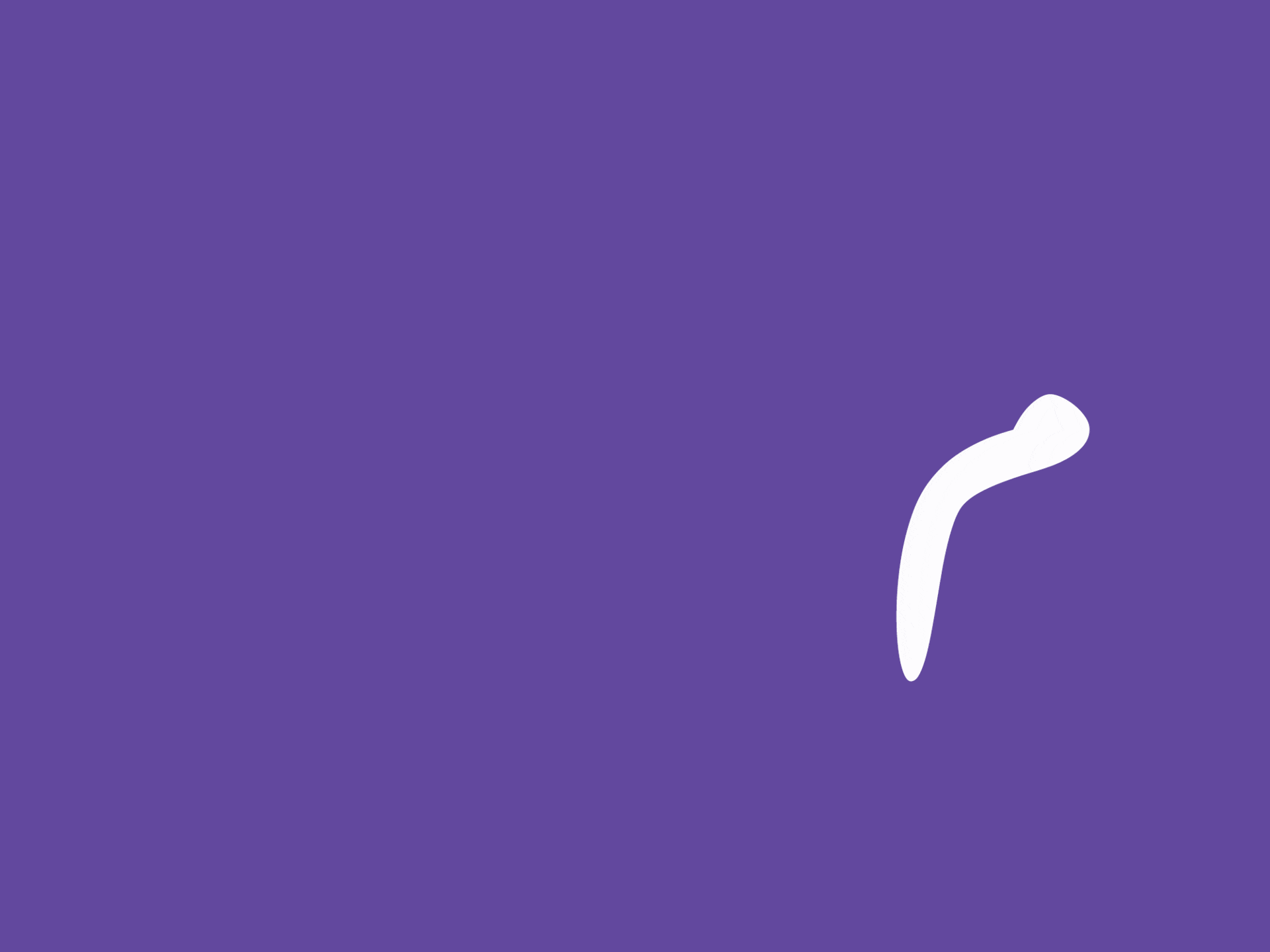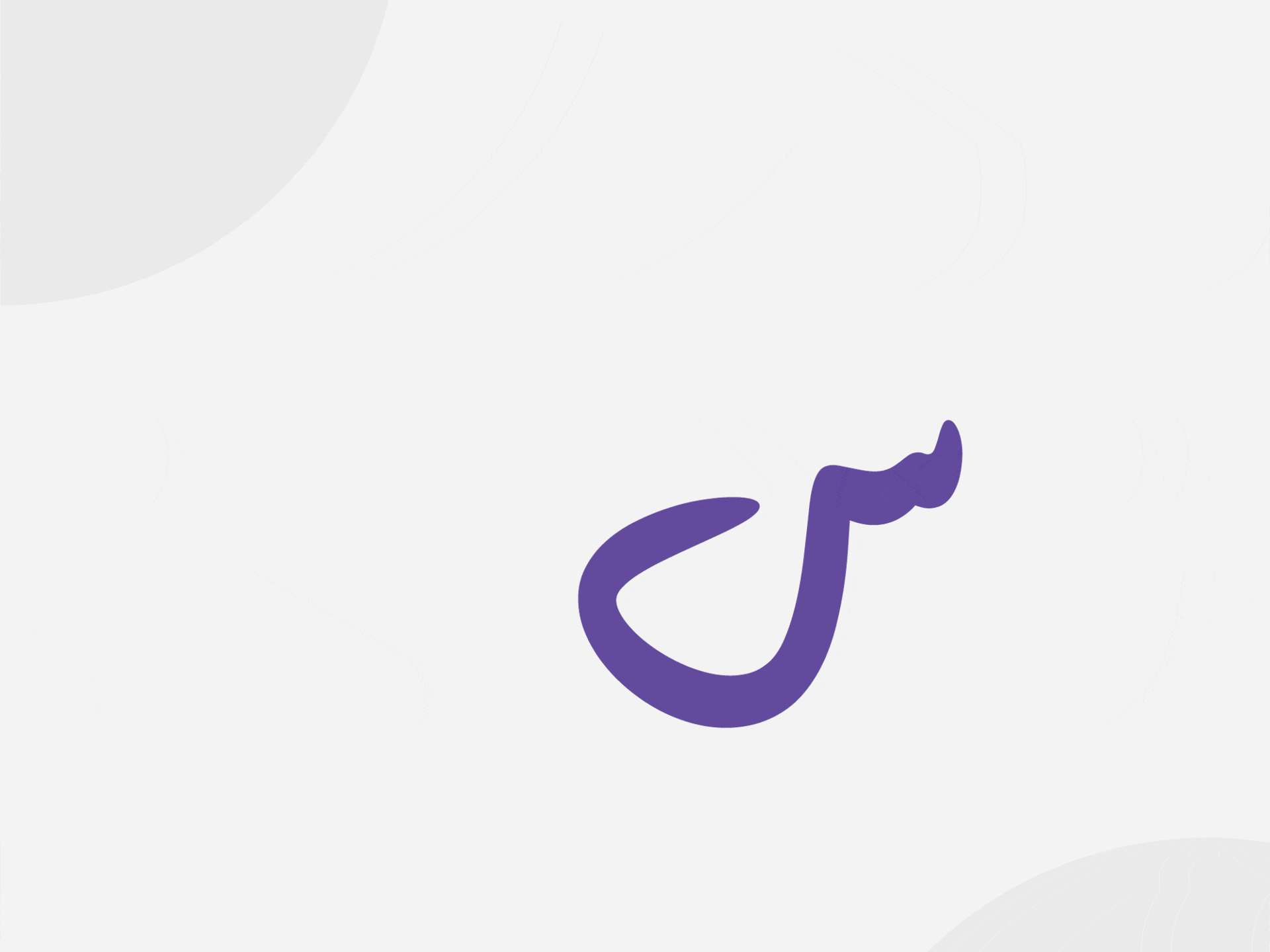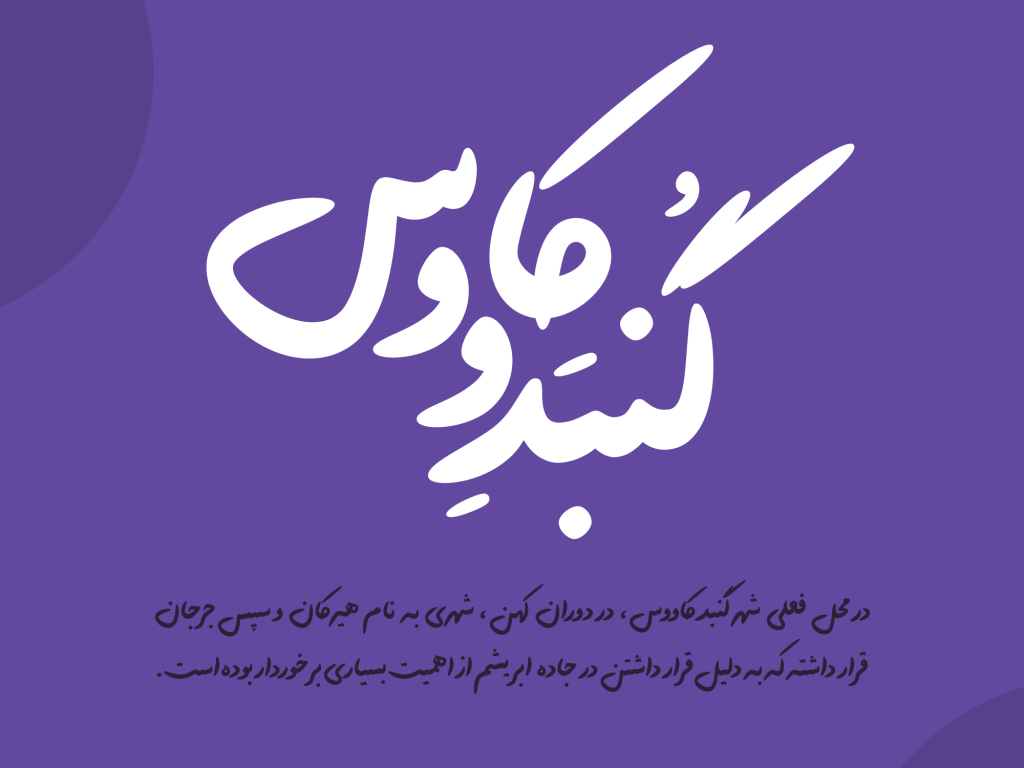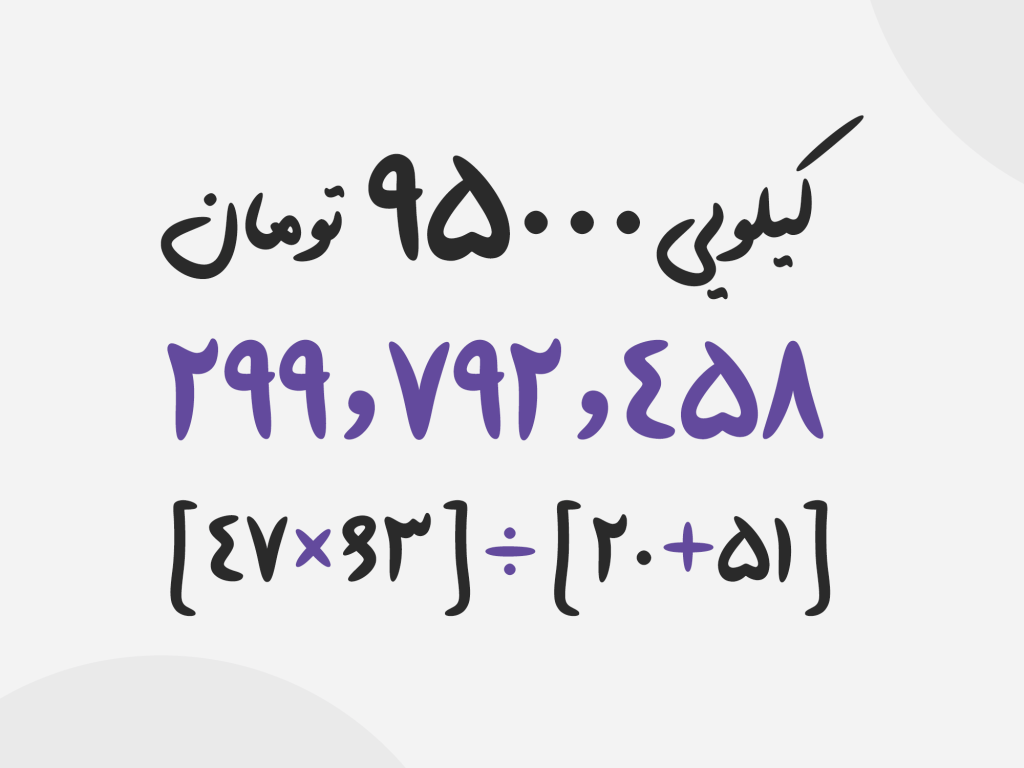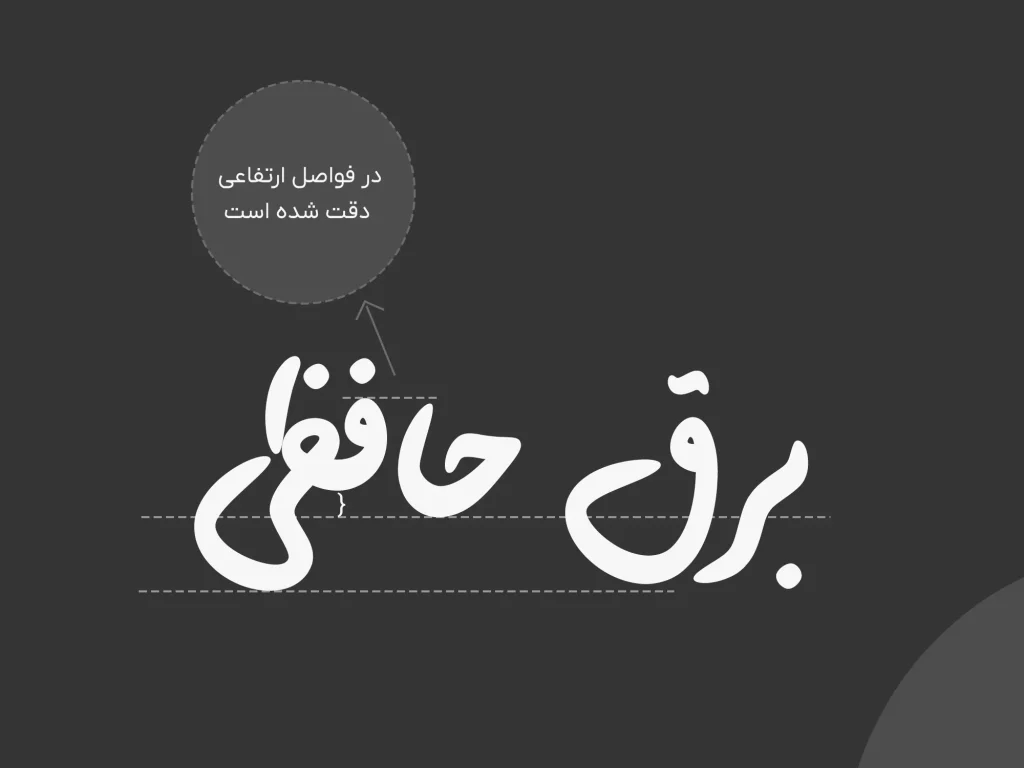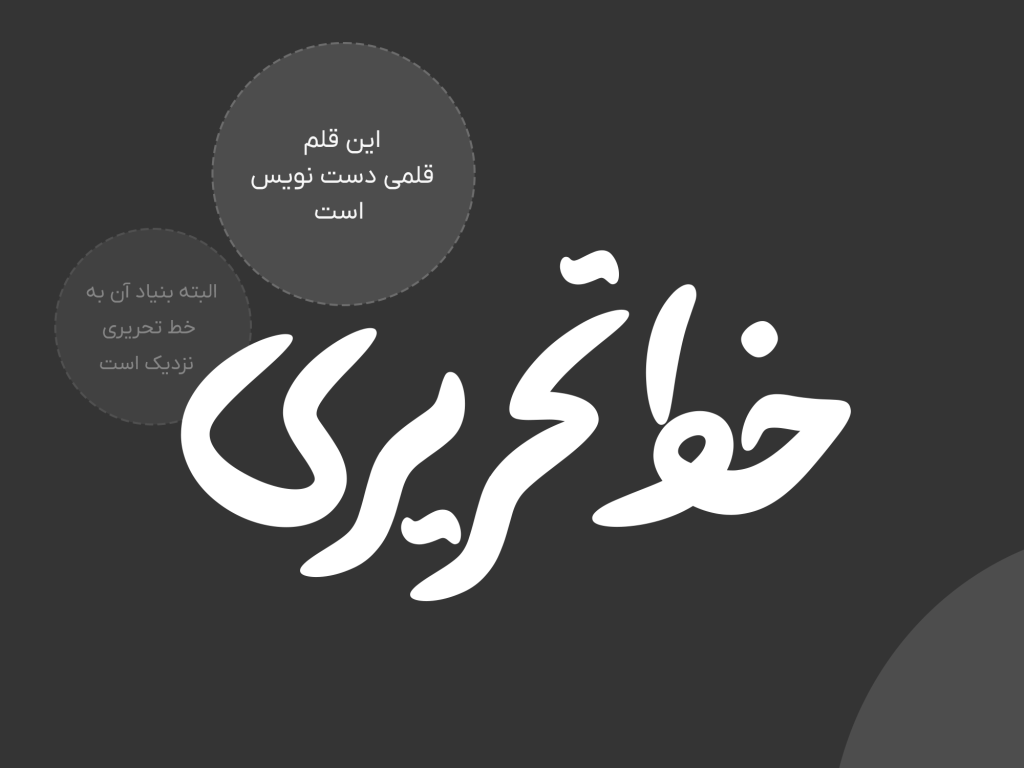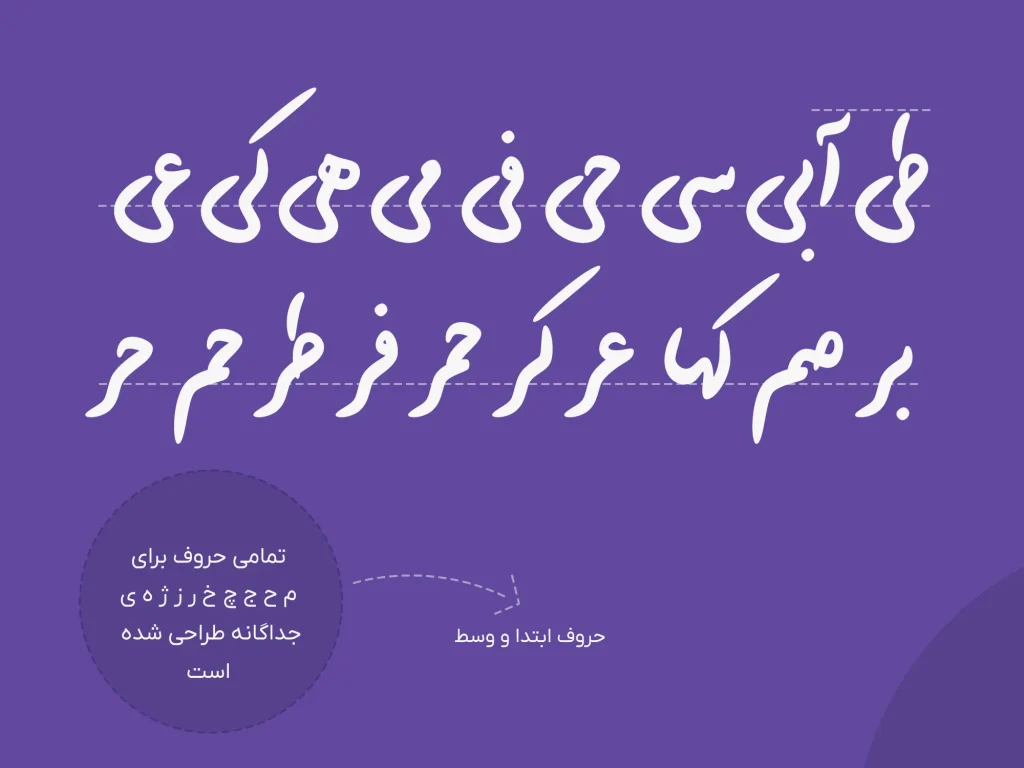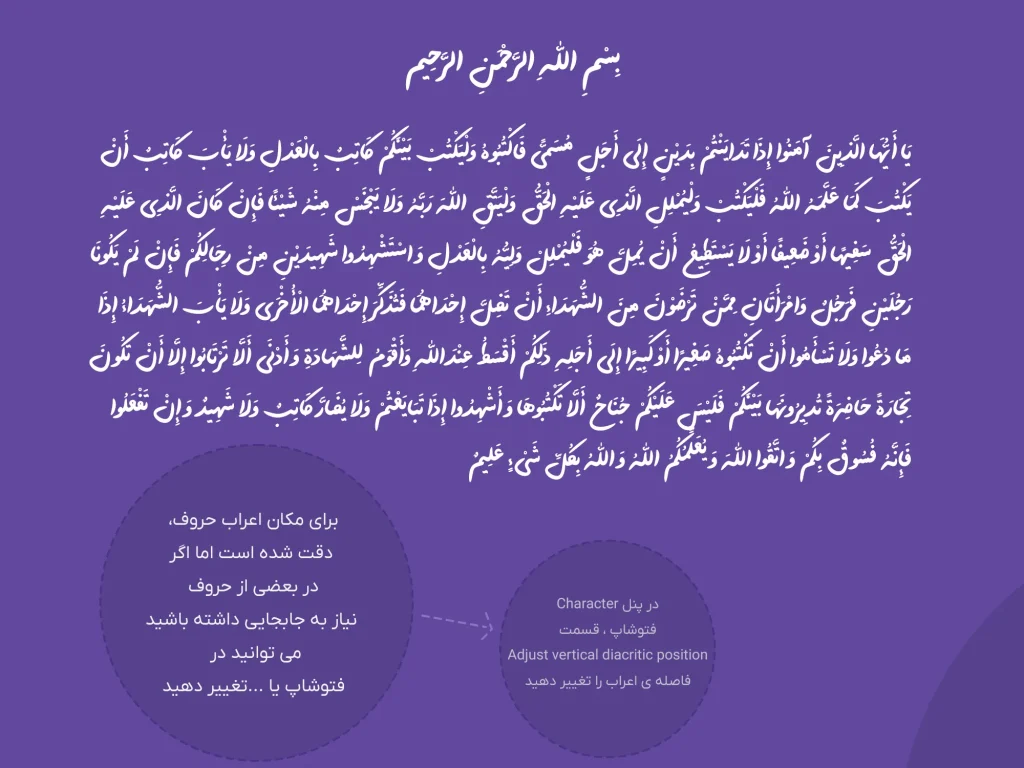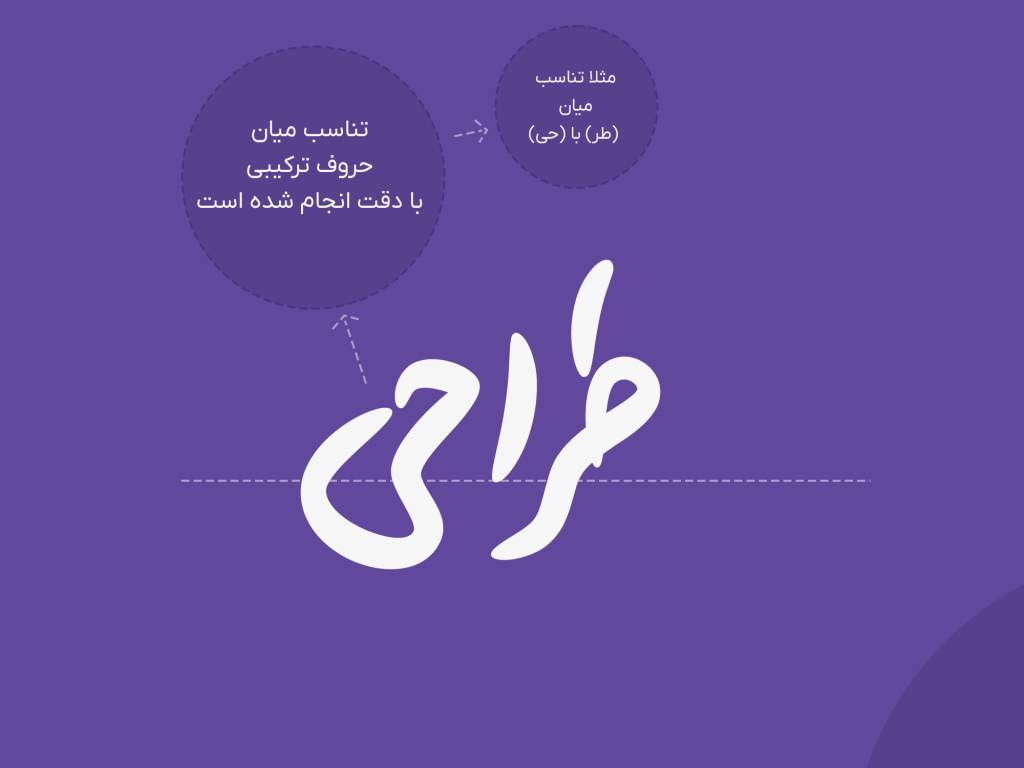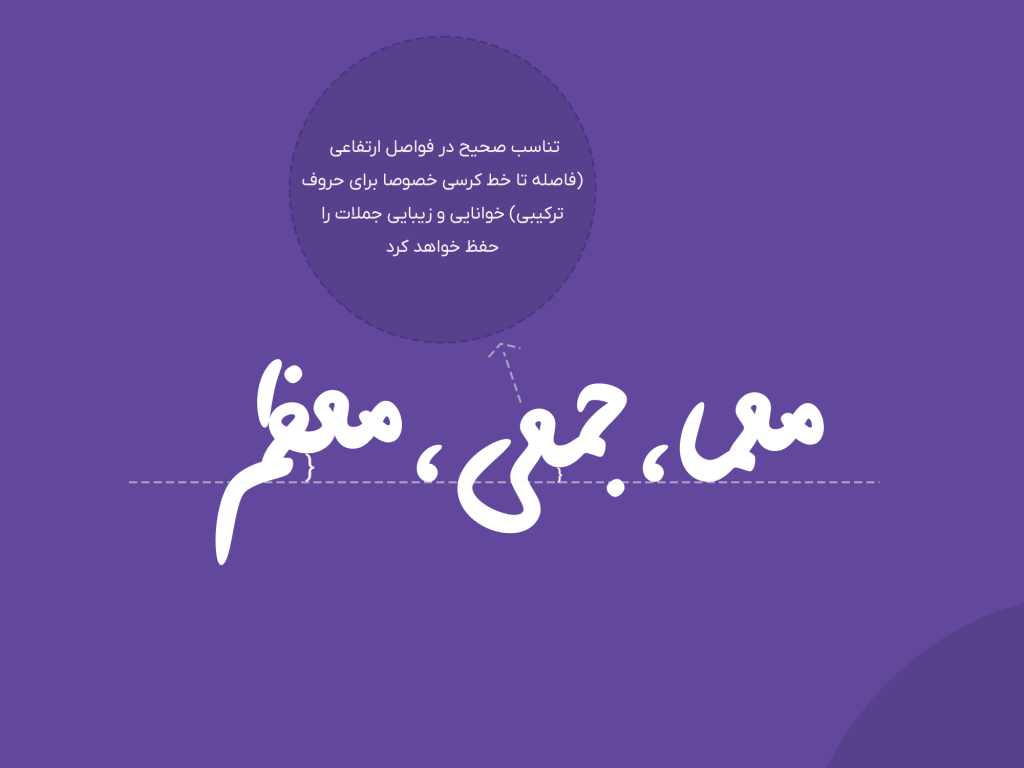
فونت پارسا از خانواده دست نویس محسوب به شمار می آید. در طراحی این قلم سال های زیادی کار شده است و اقتباس هایی از قلم نستعلیث در خود دارد.
فونت پارسا
فونت پارسا قلمی که برای طراحی آن بیش از 4 سال زمان صرف شده است. که گذراندن این مدت زمان نسبتا طولانی گواهی آشکار از میزان دقت در طراحی و توجه به جزئیات جهت متولد شدن تایپ فیسی زیبا و تاثیر گذار است. پارسا متاثر و تبعیت کننده از نوع قلمی است که با آن نوشته شده.
اگر بخواهیم از نوع و ویژگی های قلم مورد استفاده اندکی بیان کنیم می توان گفت که این قلم مانند قلم‌های خوشنویسی دارای برش‌های و لبه های تیز نیست و از حیث و نقطه نظر ضخامت تنوع کمی دارد. همچنین به نسبت قلم‌های تحریری (خودکاری) بولد‌تر است.
از دیگر تفاونت های پارسا با فونت‌های تحریری، نزول کمتر در حروف زیر خط کرسی است. که سبب می‌شود ترکیبات پراکندگی کمتری داشته باشد.
نسخه های آپدیت شده قلم پارسا
اما اگر بخواهیم قلم های همانند و هم خانواده از فونت پارسا را به شما عزیزان معرفی کنیم می توان به فونت جوان و فونت آوینی اشاره نمود . هردوی آنها همانند پارسا دارای شخصیتی پرشور و فعال و کوشا می باشند . علاوه بر اینکه ویژگی بارز دیگر نمایشی بودن پارسا می باشد که همواره به دنبال جذب نگاه خوانندگان و بینندگان به خود می باشد.